20 melhores fontes do time do colégio 2023 (gratuitas e premium)
Publicados: 2023-09-15Você é um designer gráfico em busca da fonte perfeita para aprimorar o design do seu projeto? Não procure mais!
Nesta postagem do blog, compartilharemos as 20 melhores fontes universitárias que você pode usar em 2023, quer você prefira opções gratuitas ou premium.
Compreendemos a importância de encontrar a fonte certa para elevar seus designs e estamos aqui para ajudá-lo a descobrir a combinação perfeita. Então, vamos mergulhar e explorar o mundo das fontes universitárias juntos!
Agora, você deve estar se perguntando por que vale a pena considerar as fontes universitárias. Bem, deixe-me compartilhar algumas estatísticas interessantes com você. Você sabia que usar a fonte certa pode aumentar a legibilidade e o impacto do seu design em até 80%? É verdade!
As fontes desempenham um papel crucial na transmissão do tom e da mensagem do seu projeto. Esteja você trabalhando em um design relacionado a esportes, um logotipo com tema retrô ou um convite divertido, as fontes universitárias podem adicionar um toque de nostalgia e estilo.
Com tantas opções disponíveis, você certamente encontrará uma que complemente perfeitamente a sua visão.
Neste artigo, apresentaremos as 20 melhores fontes universitárias para 2023. Organizamos uma lista de opções gratuitas e premium, garantindo que haja algo para todos, independentemente do seu orçamento.
Esteja você procurando uma fonte ousada e impactante, uma escolha limpa e moderna ou uma opção mais divertida e decorativa, nós temos o que você precisa.
Entendemos que cada projeto é único e queremos fornecer a você uma ampla variedade de fontes para você escolher. Então, vamos mergulhar e explorar essas incríveis fontes universitárias que levarão seus designs para o próximo nível!
Neste artigo, apresentaremos as 20 melhores fontes universitárias disponíveis em 2023. Essas fontes são perfeitas para designers gráficos que desejam adicionar um toque de nostalgia e estilo aos seus projetos.
Ofereceremos opções gratuitas e premium, para que você possa encontrar a fonte perfeita, independentemente do seu orçamento.
Então, se você está trabalhando em um design relacionado a esportes, um logotipo de inspiração retrô ou qualquer coisa parecida, estamos aqui para ajudá-lo a encontrar a fonte ideal para o time do colégio. Vamos começar e descobrir a fonte perfeita para aprimorar seus projetos de design!
Melhores fontes premium do time do colégio
Você é um designer gráfico que deseja levar seus projetos para o próximo nível? Nesse caso, você definitivamente vai querer conferir nossa seleção das melhores fontes premium do time do colégio.
Essas fontes irão adicionar um toque de estilo e exclusividade aos seus designs, fazendo com que se destaquem da multidão. Então não perca, continue lendo e descubra a fonte perfeita para o seu próximo projeto.
time do colégio esportivo
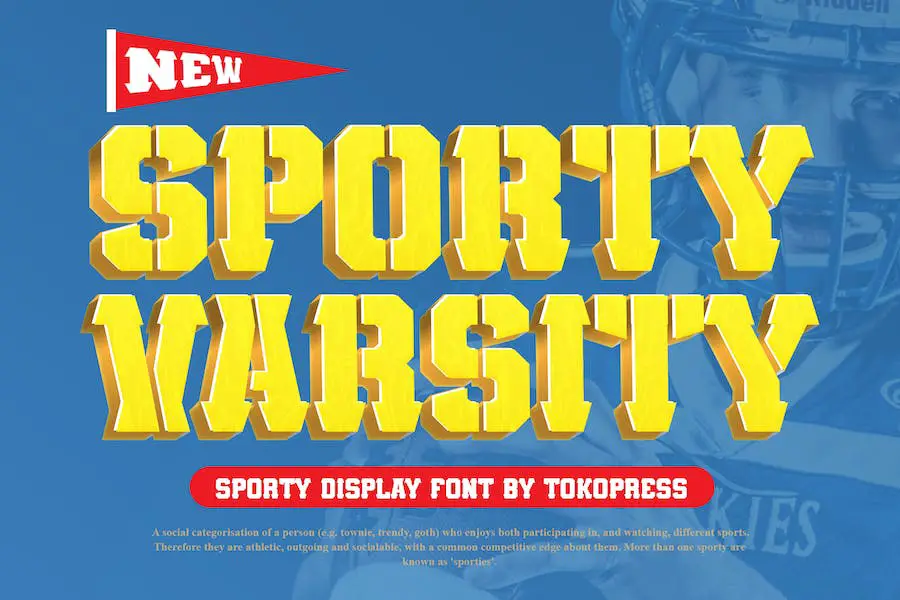
Sporty Varsity é uma fonte que exala energia e entusiasmo. É perfeito para designers gráficos que desejam adicionar um toque esportivo aos seus projetos.
Um dos principais atributos do Sporty Varsity é a sua versatilidade. Ele pode ser usado para diversos fins de design, tornando-o um recurso valioso em sua coleção de fontes.
A fonte tem uma presença forte e ousada que chama a atenção instantaneamente. Seus contornos conferem-lhe uma aparência distinta, única e atraente. Isso o torna perfeito para criar manchetes e títulos impactantes.
Gato selvagem
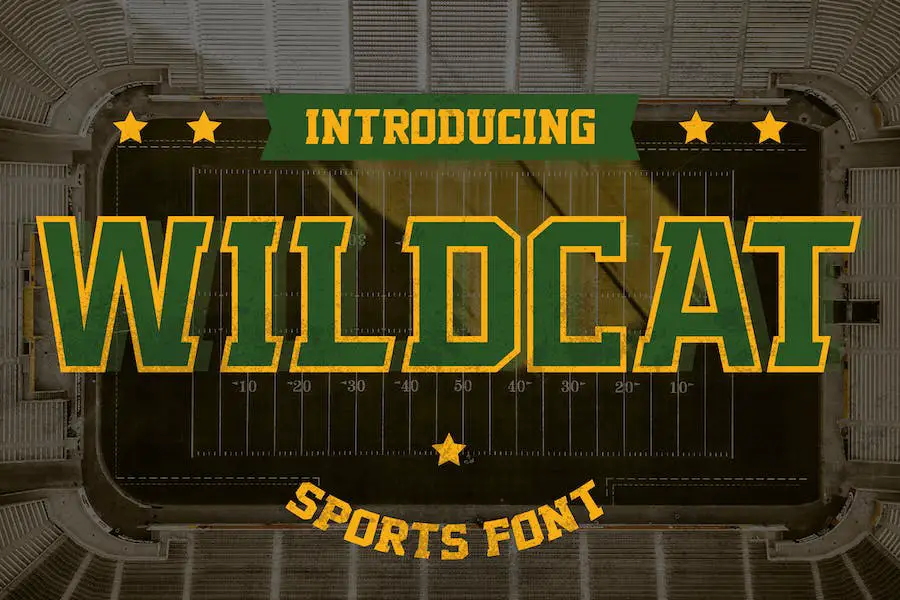
Wildcat é uma fonte atlética ideal para vários projetos relacionados a esportes, como basquete, futebol, softball e muito mais.
Esteja você criando logotipos, pôsteres, roupas ou etiquetas, esta fonte dará às suas criações uma aparência ousada e poderosa. Com sua versatilidade e impacto, Wildcat é essencial para qualquer designer gráfico que busca elevar seus designs com temática esportiva.
Faculdade
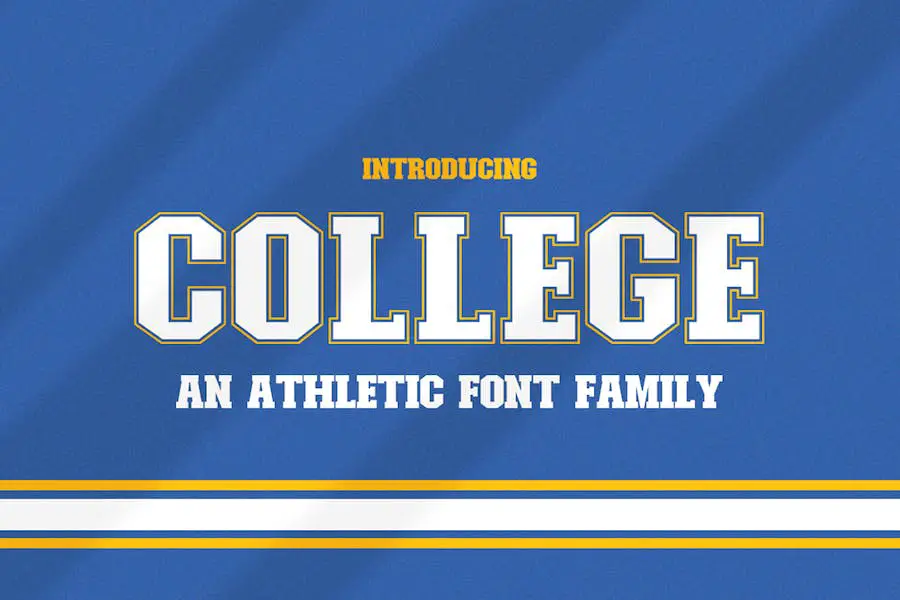
College é uma família de fontes fantástica que traz aos seus designs um toque lúdico e vibrante. Você pode misturar e combinar as fontes para criar combinações exclusivas e ficar à vontade para experimentar cores para adicionar ainda mais entusiasmo.
É como ter um grupo de amigos sempre prontos para trazer alegria universitária aos seus projetos!
Com a faculdade, as possibilidades são infinitas. Esteja você trabalhando em um logotipo de time esportivo, em um pôster de evento escolar ou até mesmo em um gráfico divertido para mídia social, essas fontes certamente aumentarão a energia e chamarão a atenção de todos.
Bruisers
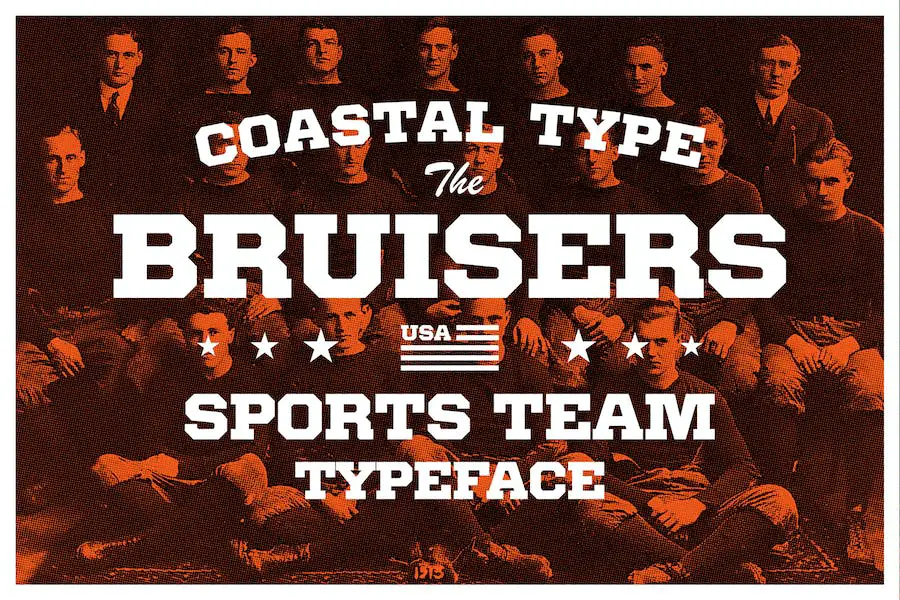
Bruisers é uma fonte com serifa forte e ousada que se inspira nos esportes universitários, universitários e universitários, bem como na rica história dos times esportivos americanos.
Além disso, Bruisers é compatível com programas populares de processamento de texto, como Microsoft Word e Canva, tornando-o acessível a um público mais amplo. Com apenas alguns cliques, você pode incorporar facilmente essa fonte em seus documentos de arquivo, apresentações ou postagens em mídias sociais, dando-lhes personalidade e estética distintas.
Pinte-o na sua pele para um tributo vitalício ao seu time favorito ou adicione um toque único aos seus projetos de circuito. A versatilidade do Bruisers permite transcender as aplicações de design tradicionais, tornando-o uma escolha perfeita para tatuagens e placas de circuito.
Faculdade de calouros
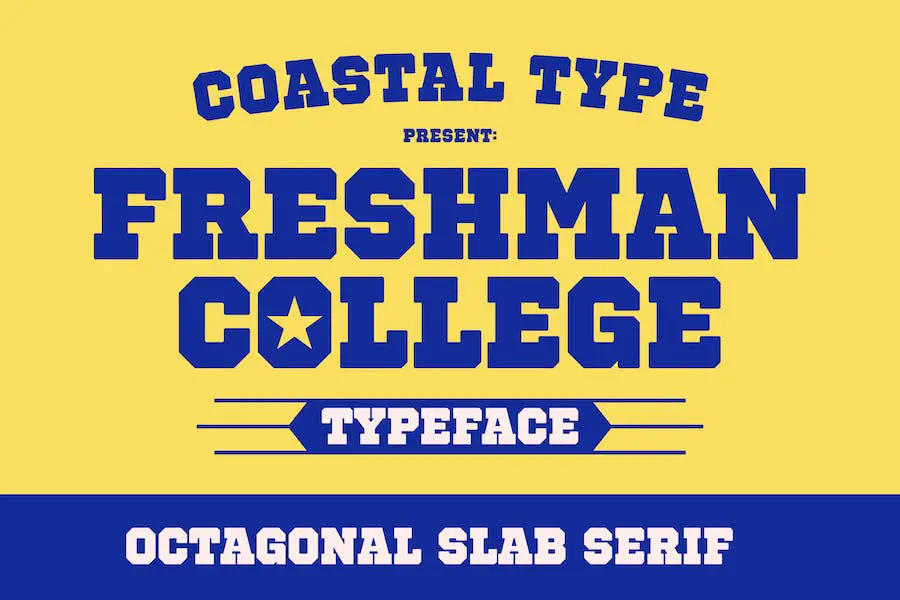
Freshman College é uma fonte de exibição impressionante que incorpora o espírito do time do colégio, da faculdade, dos esportes universitários e da estética militar.
Perfeita para designs relacionados a esportes, logotipos de times, instituições educacionais e trabalhos de exibição atraentes, esta fonte com serifa octogonal é versátil e impactante.
Esteja você criando citações, pôsteres, siglas ou manchetes, Freshman College é a fonte que elevará seus projetos ao próximo nível. Sua vibração atlética e autoritária certamente deixará uma impressão duradoura.
Cão de acampamento
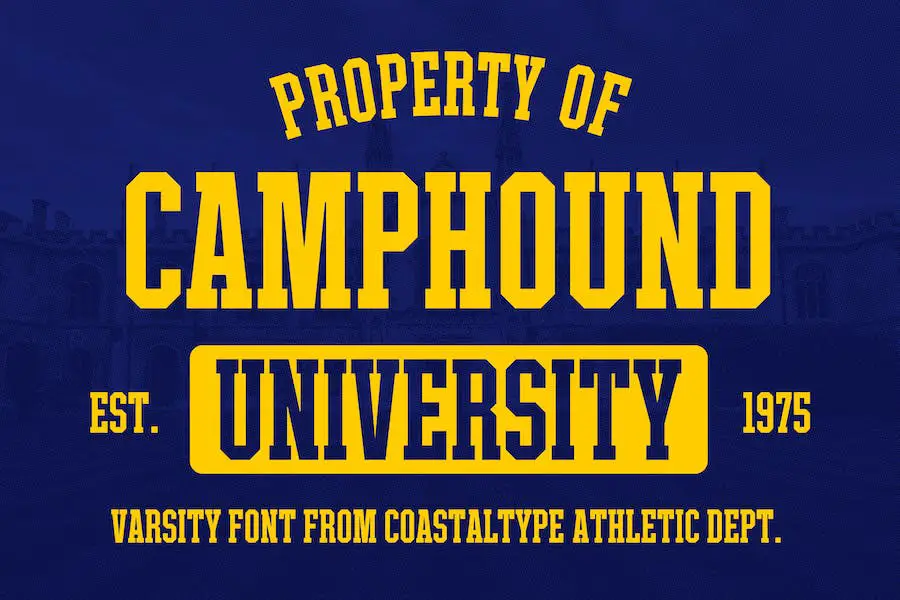
Camphound é uma fonte serifada que se inspira nos esportes universitários, universitários e universitários, bem como nos militares.
Com seu design arrojado e impactante, é perfeito para aprimorar projetos esportivos, equipes esportivas, escolas e trabalhos de exibição. Esteja você criando citações, pôsteres, siglas ou títulos, Camphound adiciona um toque energético e dinâmico aos seus designs.
Bronzeador
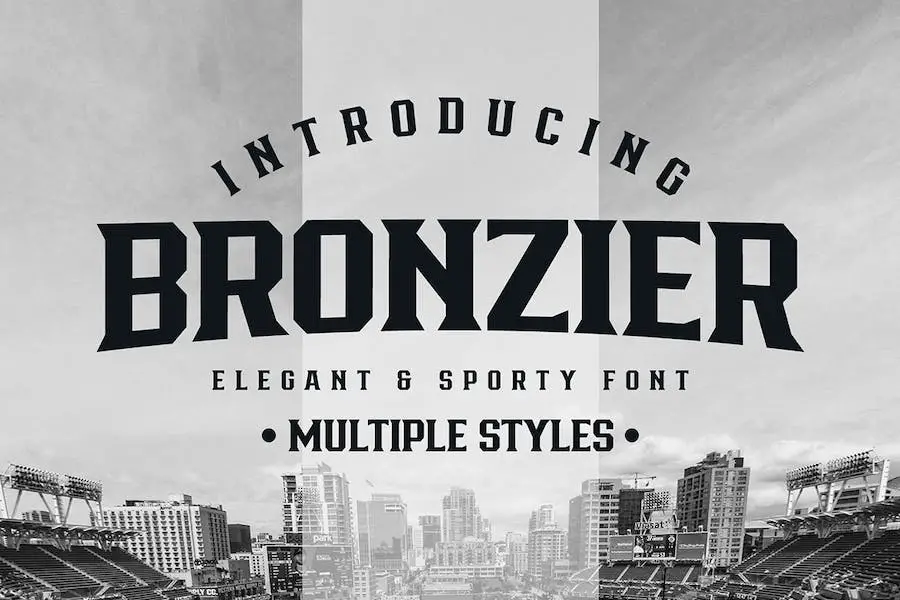
Bronzier é a fonte que você precisa para levar seus projetos de design para o próximo nível. Projetada especificamente para designers gráficos, esta fonte com serifa forte oferece 8 estilos diferentes que atendem a diversas necessidades de design.
Esteja você trabalhando em um logotipo, roupa, camisa, etiquetas, etiqueta, pôster, design de adesivo ou projeto de marca, a Bronzier tem o que você precisa.
Com sua serifa forte e nítida, Bronzier exala uma vibração masculina e esportiva, mantendo um toque de estética vintage e moderna.
Time do colégio do campo esportivo
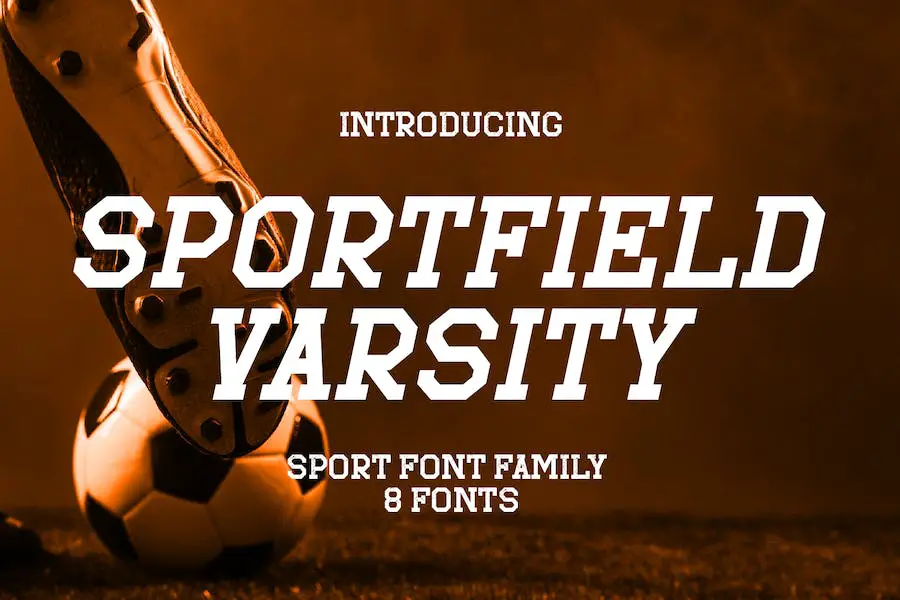
Sportfield Varsity é uma família de fontes versátil projetada especificamente para designs esportivos e esportivos.
Suas letras ousadas e angulares exalam poder e movimento, tornando-o uma excelente escolha para logotipos, manchetes e outros elementos gráficos que precisam criar um forte impacto visual.
Esteja você trabalhando em um logotipo de equipe ou criando um pôster atraente, esta fonte certamente levará seu projeto para o próximo nível.
Radley
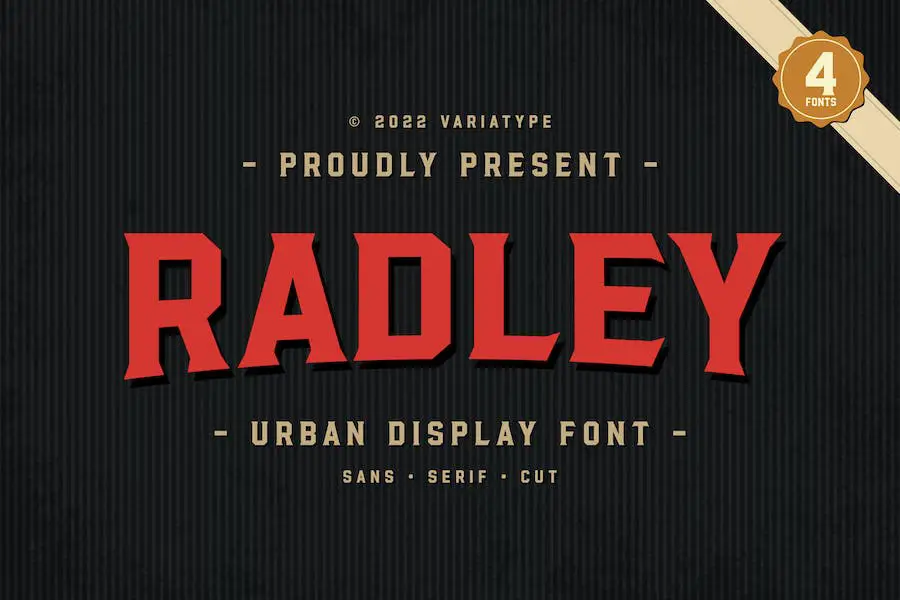
Radley é uma fonte urbana em letras maiúsculas que foi projetada especificamente para marcas e logotipos esportivos. Com seu design elegante e moderno, Radley é a escolha perfeita para designers gráficos que buscam aprimorar seus projetos e destacá-los.
Este pacote de fontes inclui não apenas uma, mas quatro fontes exclusivas e versáteis que adicionarão aquele toque extra de grandiosidade a qualquer projeto. Não perca a oportunidade de elevar seus designs com Radley – compre agora!
Breakdons
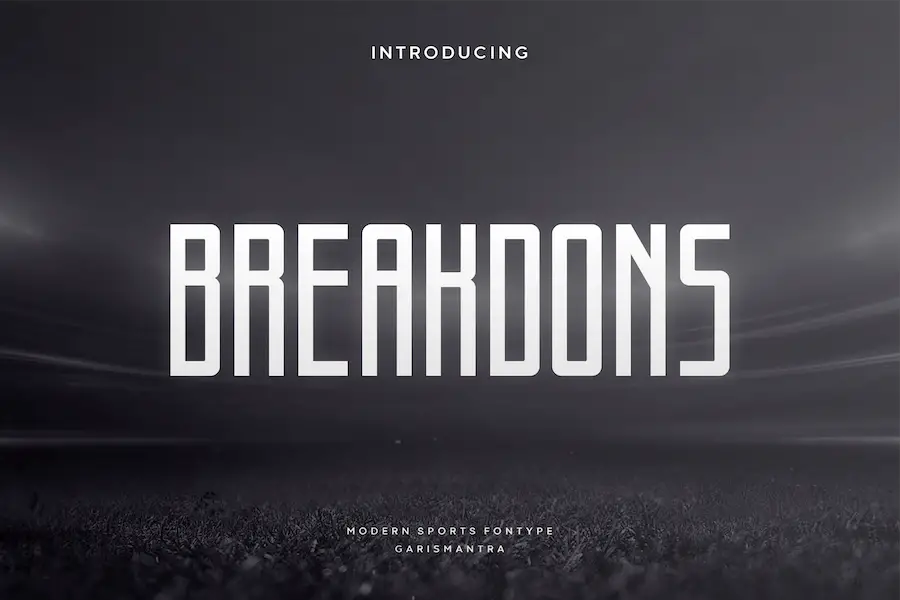
Breakdons é uma família de fontes com serifa que se inspira em tipos de formas vintage. Suas letras e contornos sólidos conferem aos designs do time do colégio uma atitude esportiva.
Esta fonte é perfeita para displays e roupas de equipe, adicionando um toque de estilo a qualquer projeto. Com seu charme retrô, Breakdons é obrigatório para designers gráficos que buscam elevar seus projetos.
Marlivane
Marlivane é uma fonte de exibição esportiva poderosa e dinâmica projetada especificamente para esportes e projetos relacionados a esportes. Possui um estilo forte e distinto que adiciona energia e impacto a qualquer design.
Quer seja para criar logótipos, gráficos para redes sociais, títulos de filmes ou livros, ou mesmo letras de texto longas, Marlivane é uma escolha versátil. Ela também serve como uma excelente fonte secundária quando combinada com fontes sans ou serif.
Com sua versatilidade e visual marcante, Marlivane é um must-have para designers gráficos que buscam valorizar o design de seus projetos.
Bellstead
Bellstead é uma fonte de exibição atlética de inspiração vintage perfeita para adicionar um toque de nostalgia e personalidade aos seus projetos de design.
Esteja você trabalhando em conteúdo relacionado a esportes, criando logotipos para times esportivos ou escolas, ou simplesmente precisando de uma fonte que se destaque para trabalhos de exibição, citações, pôsteres, siglas e títulos, a Bellstead tem o que você precisa.
Com seu estilo único e versatilidade, esta fonte certamente levará seus designs para o próximo nível.
Universidade
'Univarsity é uma fonte de exibição esportiva que impressiona. Com seu design alto e agressivo, acrescenta um toque ousado e energético a qualquer projeto de design.
Esteja você trabalhando em um título, banner, título, pôster, tipografia ou marca nominativa, esta fonte certamente fará com que se destaque. Além disso, é versátil o suficiente para ser usado em designs esportivos, atléticos, camisas, esportes eletrônicos e marcas.
Então, se você é um designer gráfico e quer levar seus projetos para o próximo nível, experimente o Univarsity'.
Esportista
Sporter é uma fonte de exibição esportiva perfeita para adicionar um toque ousado e energético aos seus designs. Com seu estilo versátil, pode ser usado para logotipos, etiquetas, crachás, manchetes, assinaturas, embalagens e muito mais. Abrace a vibração dinâmica e atlética que Sporter traz para seus projetos.
Melhores fontes gratuitas do time do colégio
Quer adicionar um pouco de talento e personalidade aos seus designs? Confira nossa seleção das melhores fontes universitárias gratuitas!
Essas fontes trarão uma vibração nostálgica e esportiva aos seus projetos, elevando seu design geral e fazendo com que se destaquem. Dê uma olhada em nossas principais recomendações e prepare-se para levar seus designs para o próximo nível!
time do colégio
Quer aprimorar seus projetos de design e trazer um toque de exclusividade? Não procure mais, pois as fontes Varsity podem ser apenas o ingrediente que faltava. Projetada pela Brderbund Software, esta coleção de fontes oferece uma ampla variedade de estilos para atender a todas as suas necessidades de design.
Varsity Fonts, criada pela Brderbund Software, é uma coleção versátil que traz um novo nível de criatividade aos seus projetos de design. Esteja você trabalhando em um pôster com tema esportivo ou em um logotipo de inspiração retrô, essas fontes foram projetadas para destacar seu trabalho da multidão.
Com uma ampla gama de estilos e variações, Varsity Fonts oferece algo para todos os gostos e projetos. De letras em negrito e blocos a letras elegantes e fluidas, você encontrará a fonte perfeita para combinar com sua visão.
Faculdade de Atlanta
Atlanta College é uma fonte criada pela graphicsauceco perfeita para designers gráficos que buscam aprimorar o design de seus projetos. Esta fonte traz um toque único e profissional a qualquer design, destacando-o dos demais.
Com o Atlanta College, você pode esperar uma ampla gama de atributos que o tornam obrigatório para qualquer designer. A fonte é elegante e moderna, adicionando um toque de elegância a qualquer texto. Suas linhas simples e caracteres bem elaborados facilitam a leitura, garantindo que sua mensagem seja transmitida de maneira eficaz.
O Atlanta College não oferece apenas uma aparência elegante, mas também versatilidade. Essa fonte pode ser usada para uma variedade de projetos, seja na criação de logotipos, pôsteres ou gráficos para mídias sociais. Seja qual for o meio, esta fonte se adapta facilmente, permitindo manter uma estética consistente e polida.
Manual do time do colégio
Varsity Playbook, criada por KC Fonts, é uma fonte perfeita para designers gráficos que desejam aprimorar o design de seus projetos. Esta fonte traz um toque esportivo e nostálgico a qualquer design, tornando-a ideal para projetos relacionados ao esporte, espírito escolar ou estética vintage.
Com o Varsity Playbook, os designers têm acesso a uma ampla gama de estilos e variações. A fonte inclui diferentes gramaturas, permitindo versatilidade e personalização. Esteja você procurando um visual ousado e atraente ou um design mais sutil e elegante, esta fonte tem o que você precisa.
Uma das características de destaque do Varsity Playbook é sua autenticidade. A fonte captura a essência das letras clássicas do time do colégio, evocando memórias de camisas de times e tipografia da velha escola. Adiciona um toque de nostalgia e personalidade a qualquer projeto de design.
DE VOLTA À ESCOLA
BACK TO SCHOOL é uma fonte chamada 'It Font' de Billy Argel Fonts. Esta fonte é perfeita para designers gráficos que desejam aprimorar seus projetos com um toque elegante e único.
'It Font' é uma fonte versátil que pode ser usada em uma ampla variedade de projetos de design. Esteja você trabalhando em um projeto com tema escolar ou simplesmente queira adicionar uma vibração divertida e jovem aos seus designs, esta fonte é uma ótima escolha.
Com suas letras ousadas e atraentes, 'It Font' certamente fará uma declaração em qualquer design. A fonte apresenta uma aparência desenhada à mão, dando um toque autêntico e orgânico. Adiciona um toque de personalidade e charme aos seus designs, fazendo com que se destaquem da multidão.
Mundo dos Esportes
Sports World é uma fonte desenhada por Sergiy S. Tkachenko, perfeita para designers gráficos que desejam aprimorar o design de seus projetos. Com sua aparência única e elegante, esta fonte adiciona um toque de inspiração esportiva a qualquer design.
A fonte Sports World apresenta letras ousadas e dinâmicas que capturam a energia e a emoção do mundo dos esportes. Sua aparência forte e assertiva o torna ideal para designs relacionados a esportes, como logotipos de times, pôsteres de eventos esportivos e roupas esportivas.
Os atributos da fonte incluem linhas bem definidas e bordas limpas, tornando-a altamente legível mesmo em tamanhos menores. Sua versatilidade permite que seja usado tanto para títulos quanto para corpo de texto, dando aos designers a flexibilidade de utilizá-lo em vários elementos de design.
Radley
Radley by Variatype é uma fonte Sans perfeita para designers gráficos que buscam elevar o design de seus projetos. Essa fonte oferece uma gama de atributos que podem valorizar qualquer design, tornando-a obrigatória para profissionais da área.
Com Radley, você pode esperar uma estética clean e moderna que adiciona um toque de sofisticação aos seus designs. O estilo sem serifa da fonte confere-lhe uma aparência atemporal e versátil, tornando-a adequada para uma ampla variedade de projetos.
Uma das características de destaque do Radley é a sua legibilidade. Os formatos de letras cuidadosamente projetados garantem que seu texto seja facilmente legível, mesmo em tamanhos menores. Isso é especialmente importante quando se trata de comunicar sua mensagem de maneira eficaz ao público.
perguntas frequentes
Varsity Fonts referem-se a uma coleção de fontes que imitam o estilo das letras comumente vistas em jaquetas de times universitários e logotipos de times esportivos. Essas fontes costumam ser ousadas, em blocos e têm um toque vintage, que lembra os esportes americanos clássicos.
Você pode encontrar Varsity Fonts em vários sites e plataformas online especializados em downloads de fontes. Algumas opções populares incluem Dafont, Creative Market e MyFonts. Esses sites oferecem uma ampla seleção de fontes Varsity para você navegar e escolher.
Os direitos de uso das fontes Varsity variam dependendo da fonte específica e de seus termos de licenciamento. É importante ler atentamente o contrato de licença ou os termos de uso fornecidos pelo designer ou fundição da fonte.
Algumas fontes Varsity podem ser gratuitas para uso pessoal e comercial, enquanto outras podem exigir licença ou compra para projetos comerciais. Sempre certifique-se de usar a fonte de acordo com as permissões designadas.
Conclusão
Concluindo, exploramos as 20 melhores fontes universitárias para 2023, tanto opções gratuitas quanto premium. Discutimos a importância de usar a fonte certa para aprimorar seus projetos de design gráfico e melhorar a estética geral.
Esteja você criando um logotipo esportivo, um panfleto escolar ou um pôster de inspiração vintage, essas fontes universitárias certamente adicionarão um toque de nostalgia e exclusividade aos seus designs.
Se você deseja mais inspiração e tutoriais sobre fontes e design gráfico, não deixe de conferir o blog BetterStudio. Atualizamos regularmente nosso blog com conteúdo informativo e útil para ajudar designers gráficos como você em sua jornada criativa.